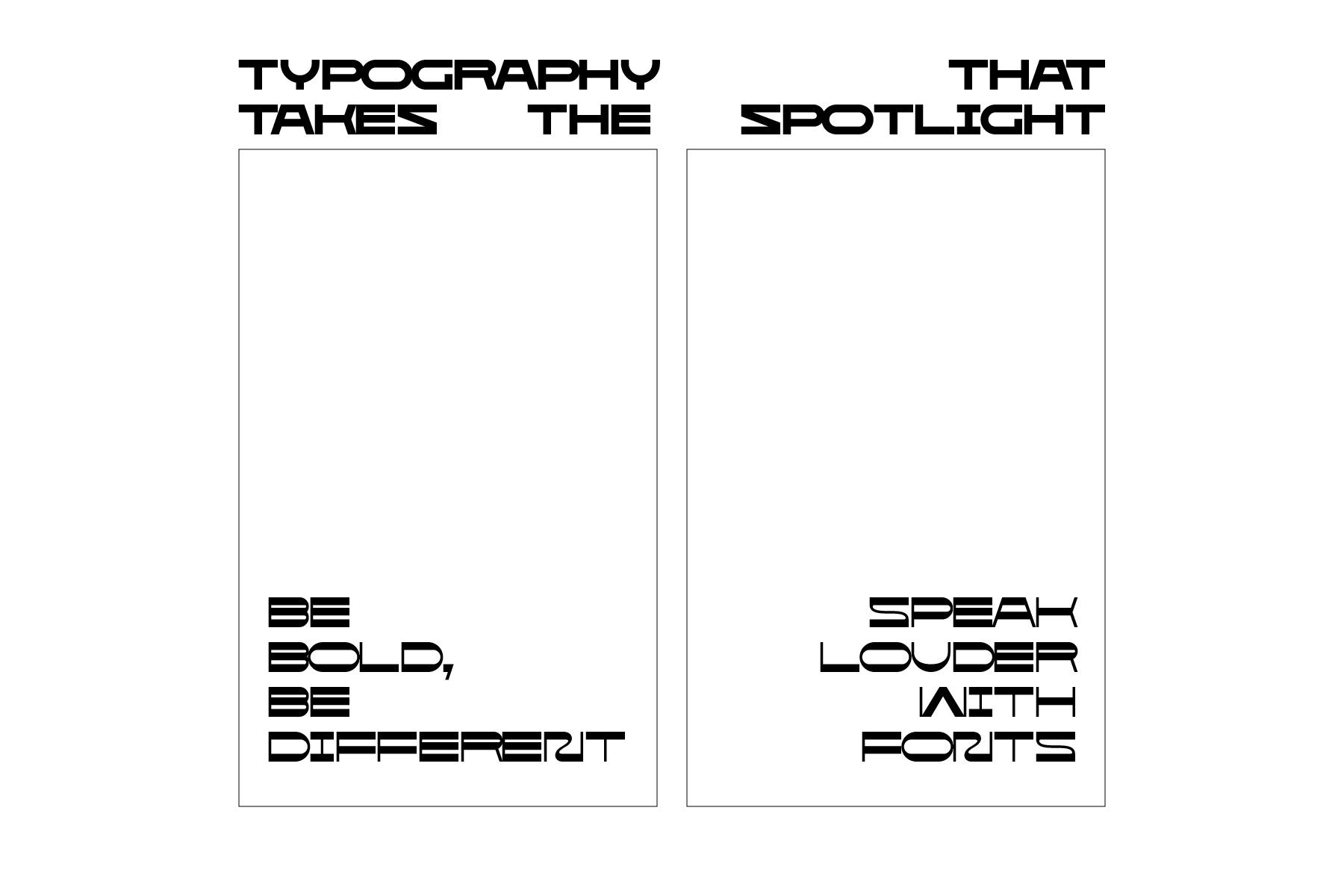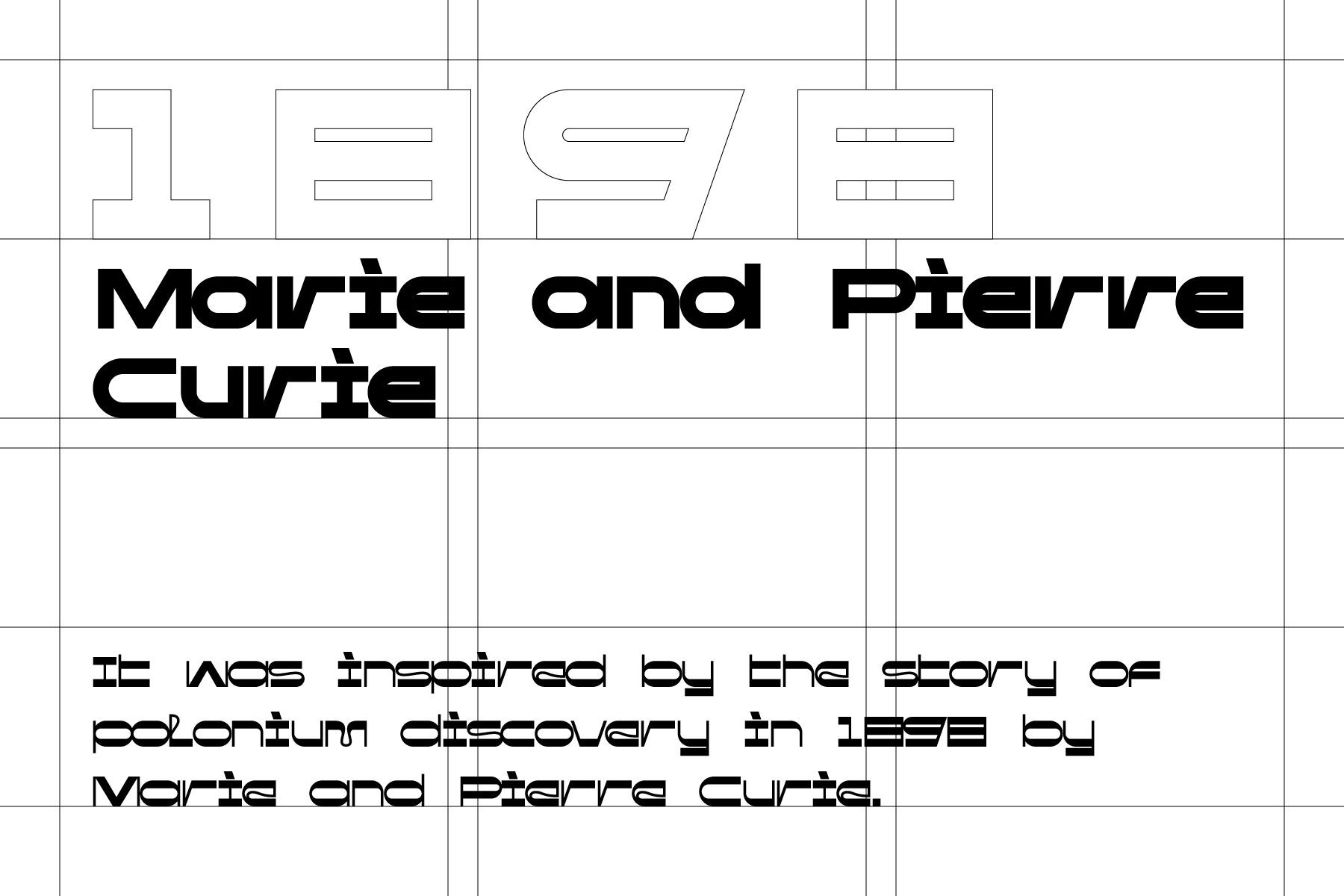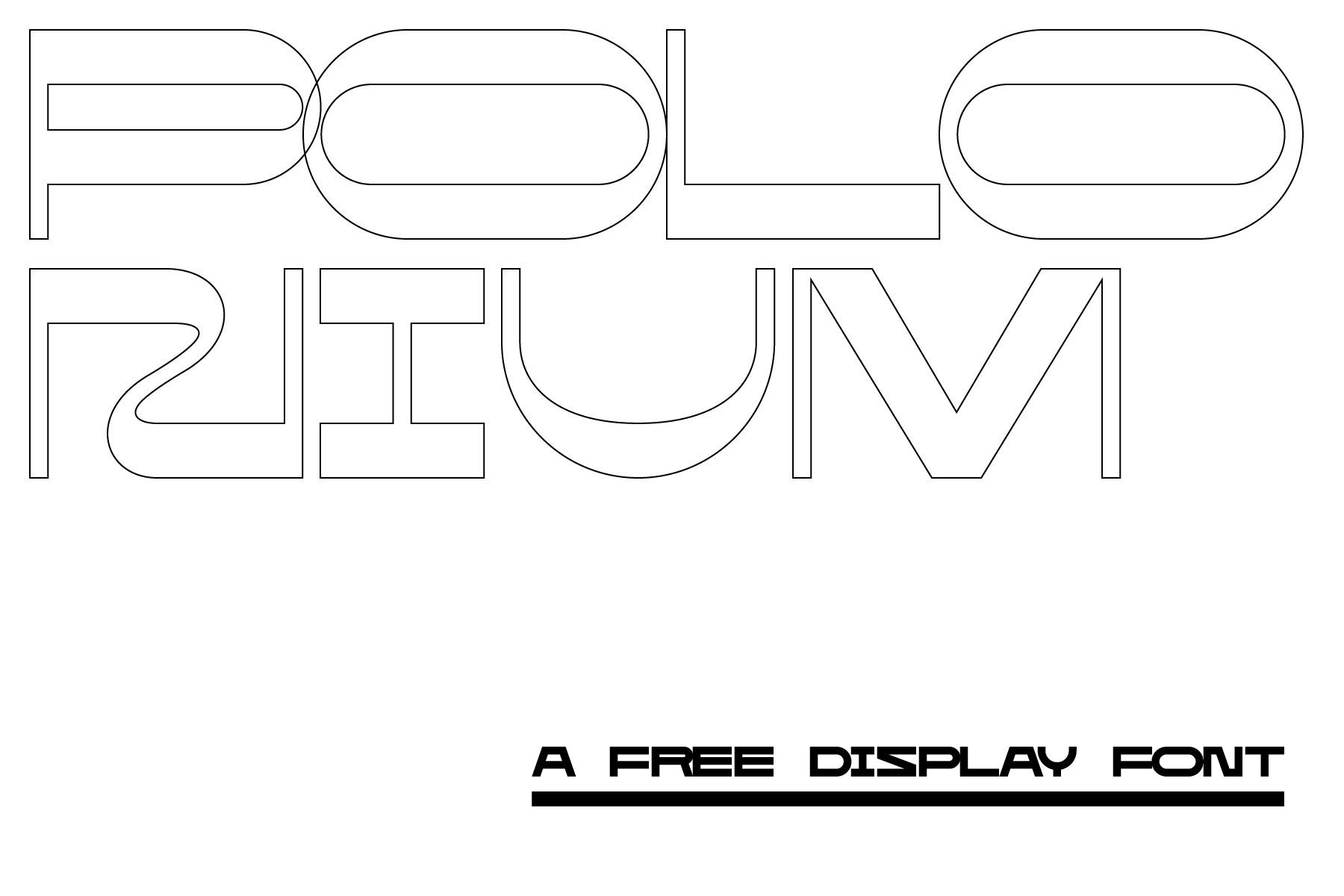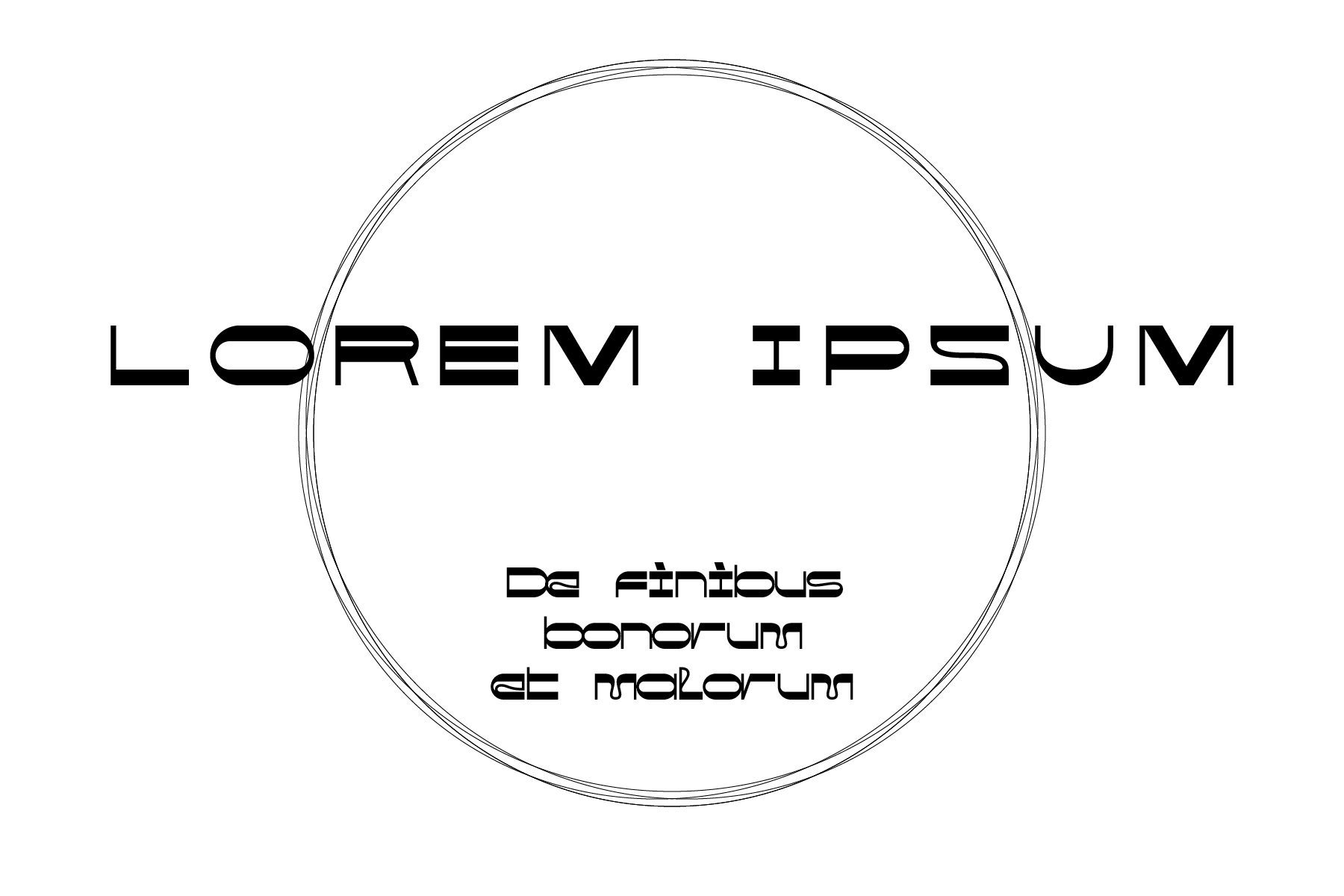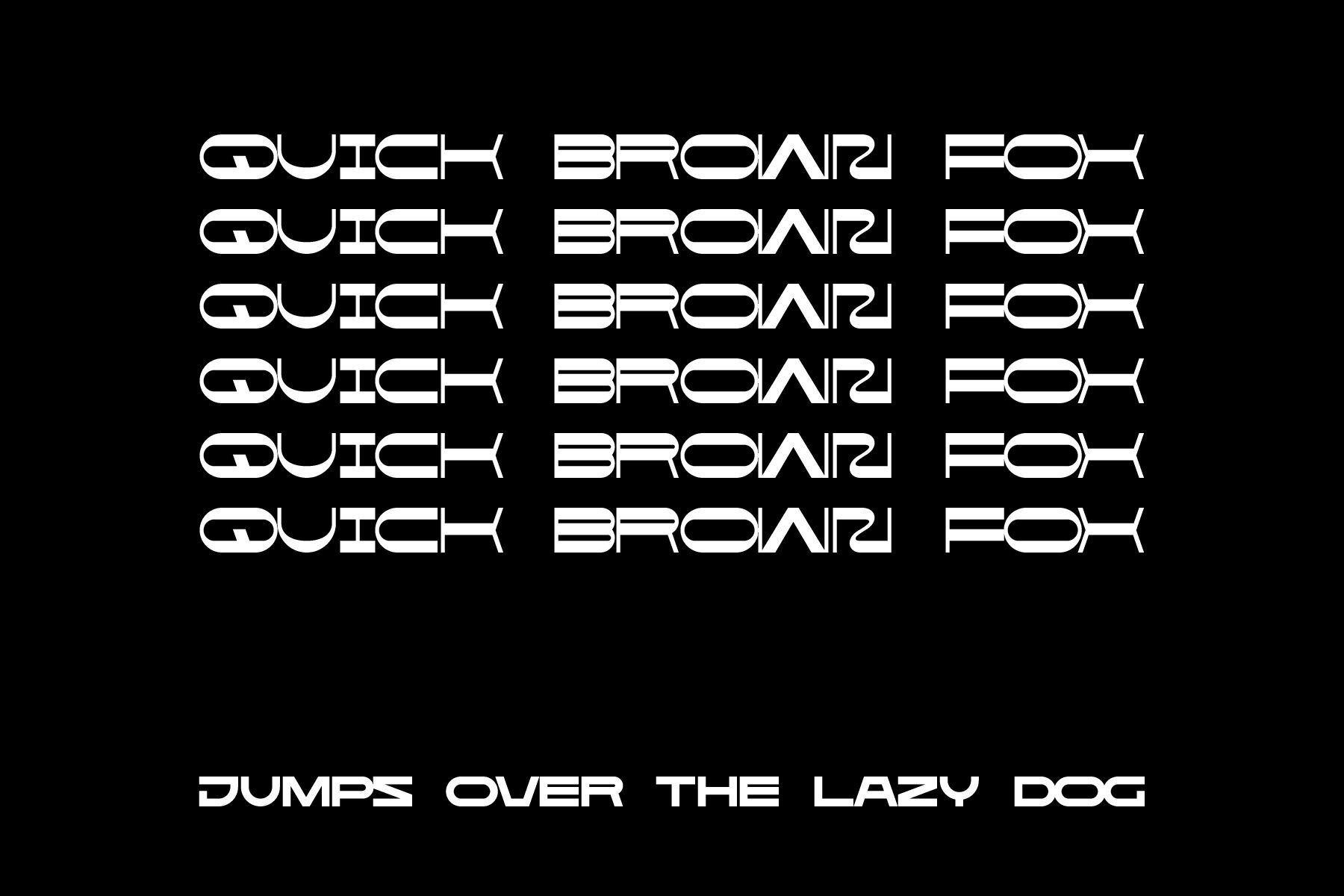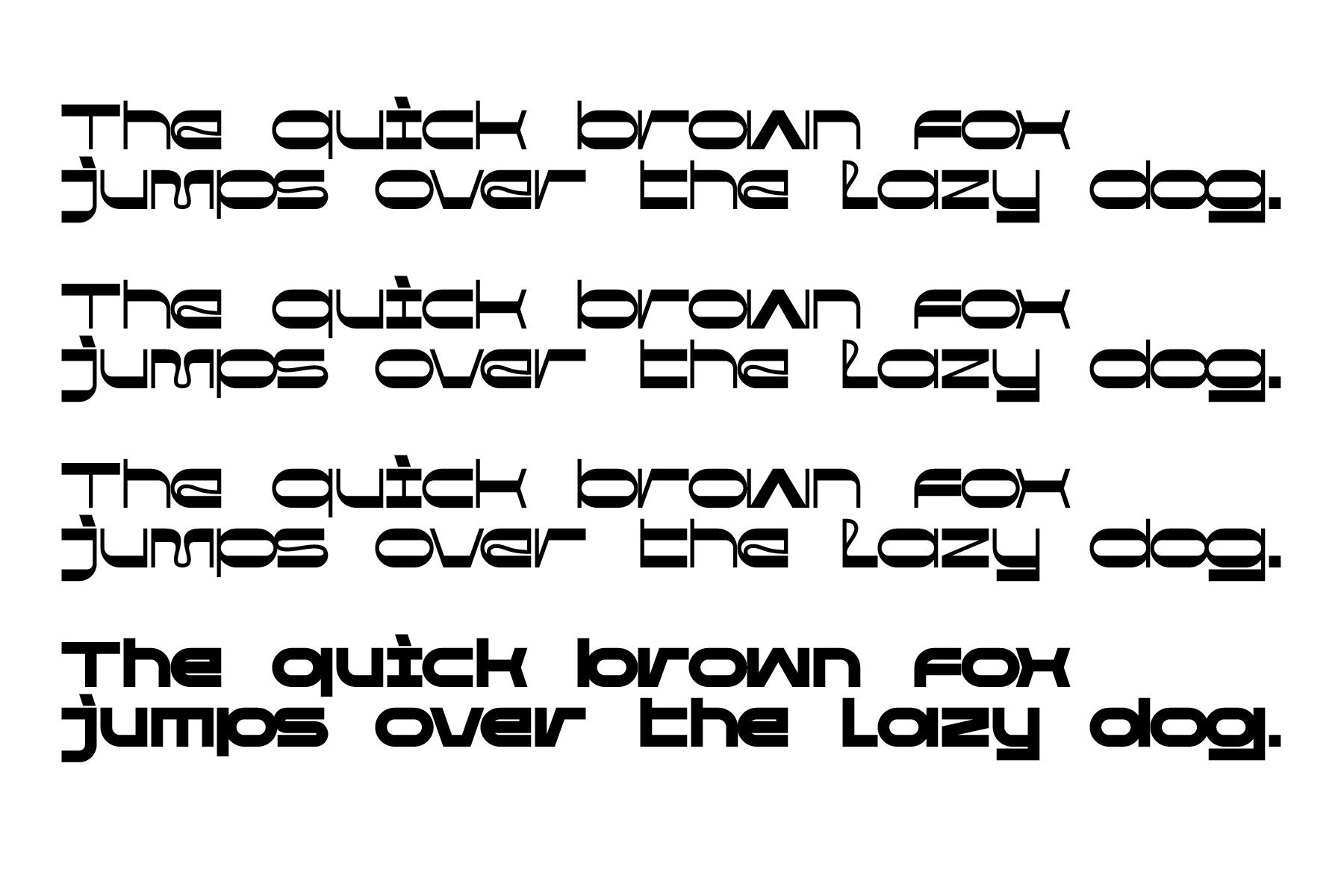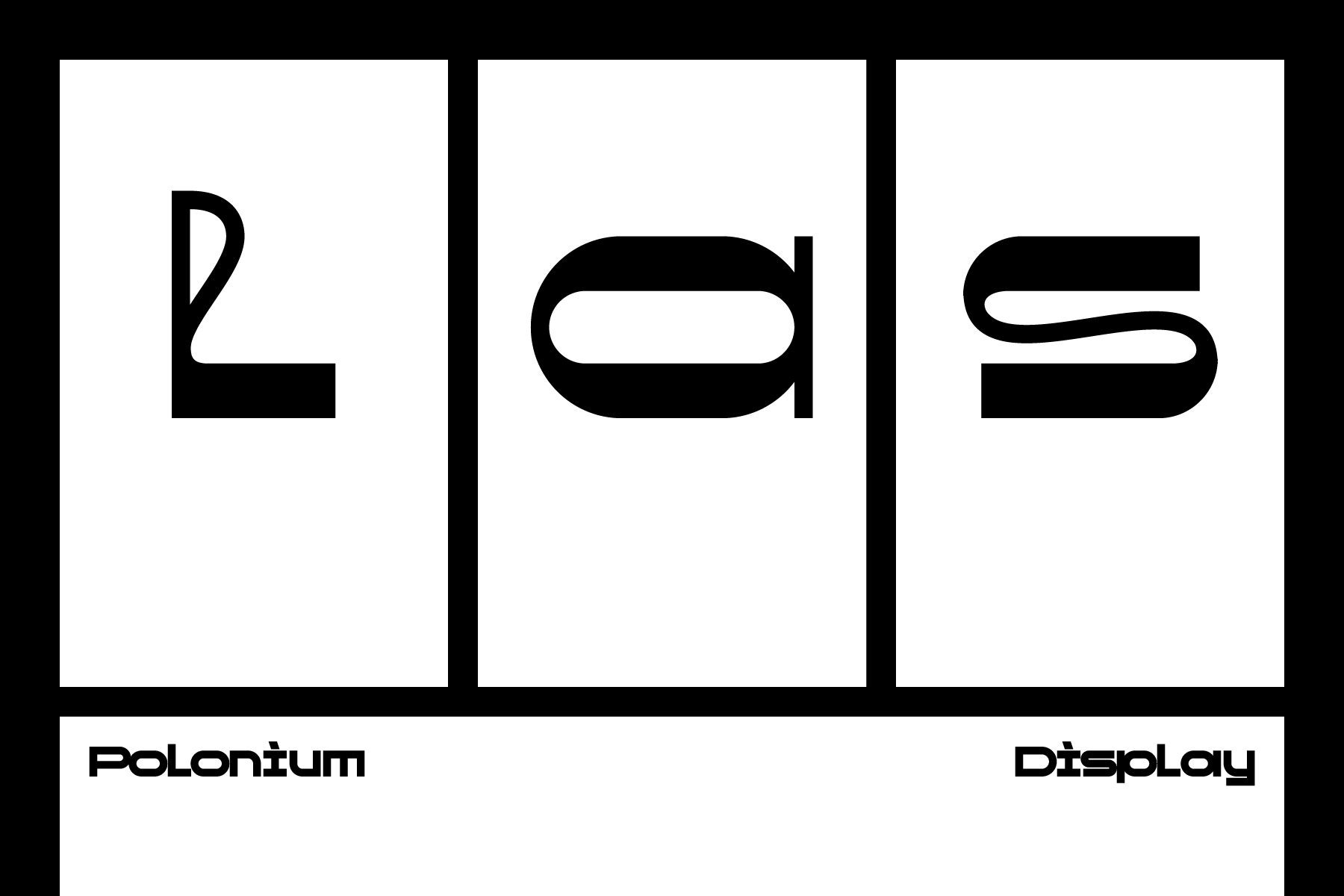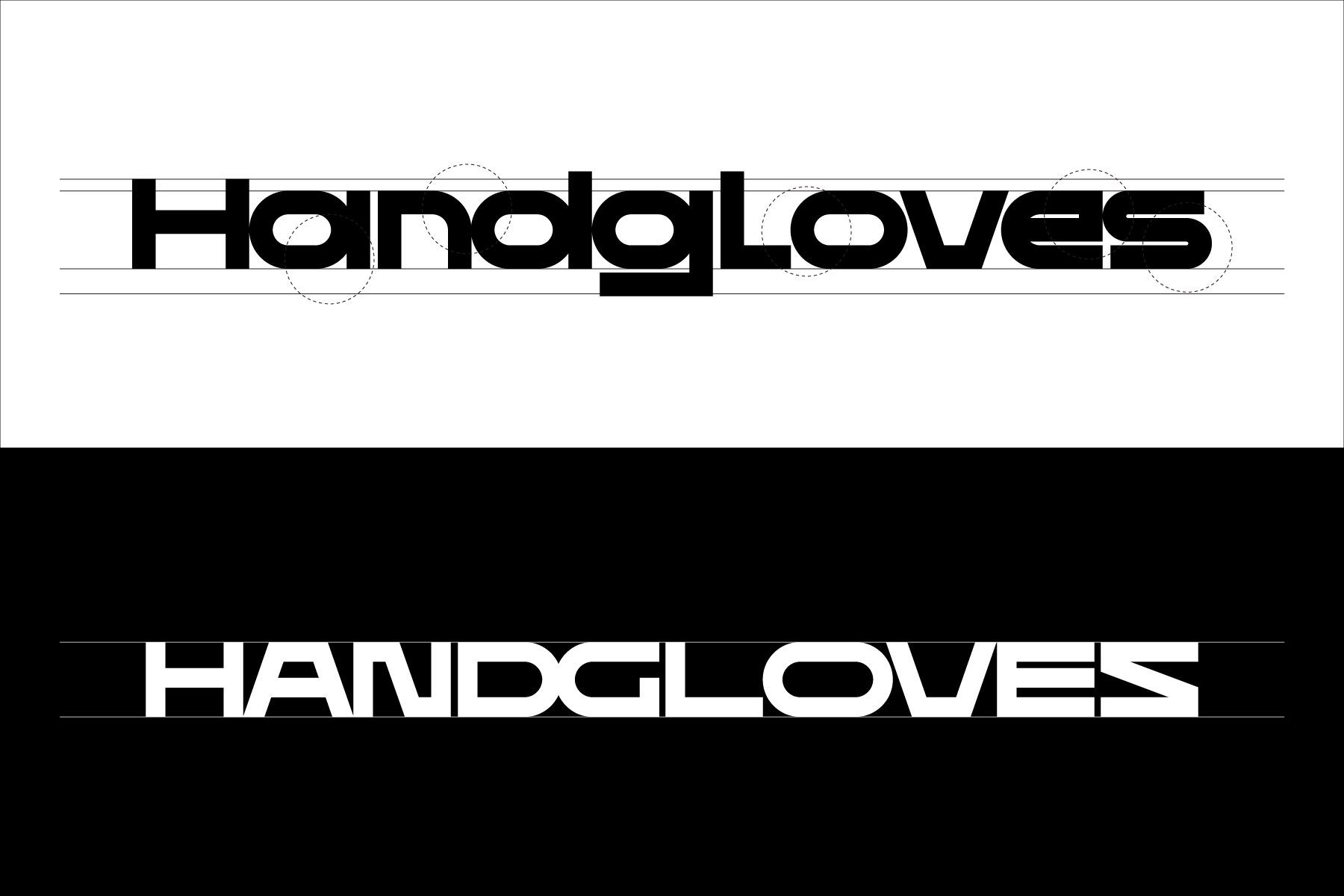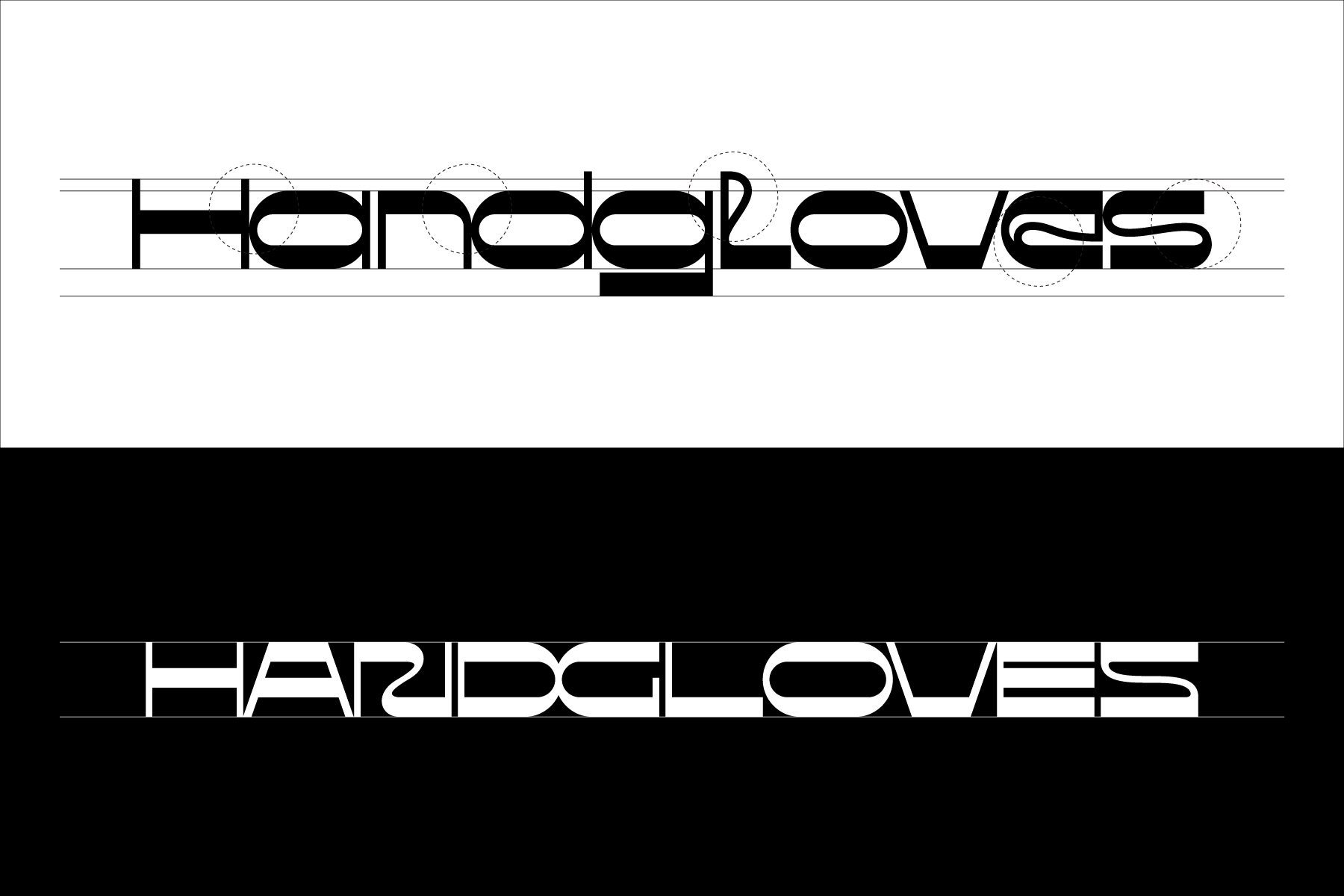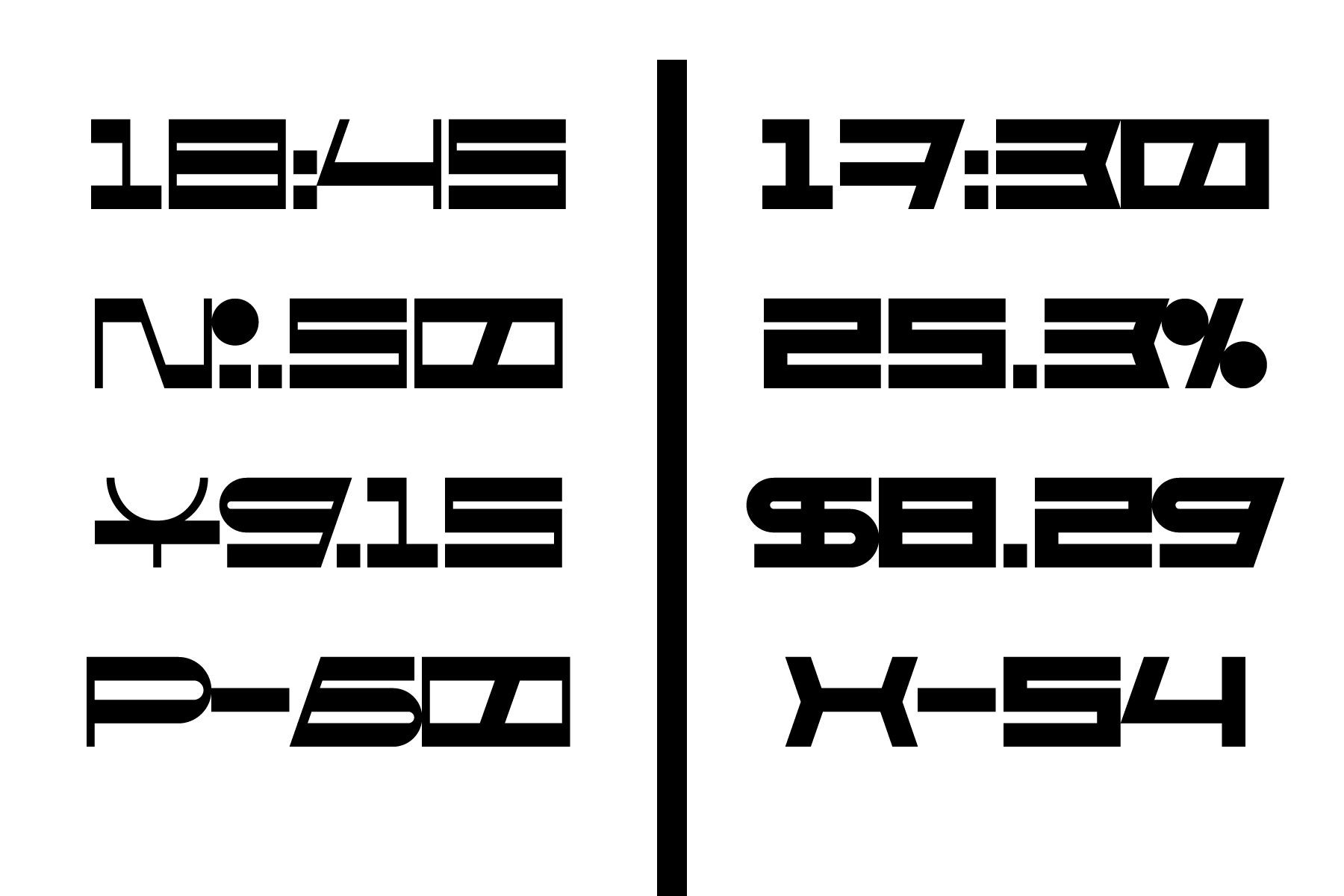
Nếu bạn đang tìm kiếm một font chữ độc đáo, cá tính mạnh để “quẩy” cùng style thiết kế Acid đang hot hit, thì không thể bỏ qua em Polonium này đâu nha!
Giới thiệu sơ qua về Polonium:
-
Nguồn gốc: Được tạo bởi Alexey Atapin.
-
Style: Siêu hiện đại, đậm chất trang trí (decorative), cá tính cực mạnh.
-
Ý nghĩa tên: Polonium chính là nguyên tố hóa học Poloni (Po) đó! Nghe tên thôi đã thấy “acid” rồi đúng không? 😉
Phân tích “nét chữ” Polonium:
-
Độ “hợp cạ” với Acid Design: Phải nói là 100%! Phong cách của Polonium cực kỳ ăn khớp với vibe méo mó, ảo diệu, đôi khi hơi “dị” của Acid Design.
-
Hai “anh em” Bold & Regular: Font này có 2 trọng lượng (weight) là Regular và Bold, nhưng không chỉ đơn giản là đậm nhạt đâu nha:
-
Bold: Nét chữ gần như đều nhau (monoline), trông khá “thô”, hình học, cứng cáp và đầy sức mạnh.
-
Regular: Có sự tương phản rõ rệt giữa nét dày và nét mỏng (ngang dày, dọc mỏng), tổng thể hình học nhưng lại có những đường cong uốn lượn, chảy, tạo cảm giác kim loại lỏng rất đặc trưng của Acid.
-
Bộ xương thống nhất, chi tiết khác biệt: Dù khác nhau về chi tiết, cấu trúc cơ bản của 2 weight này khá tương đồng, giúp chúng vừa có thể kết hợp ăn ý, vừa có thể đứng riêng lẻ phối với font khác mà vẫn nổi bật.
-
Kerning (Khoảng cách chữ) siêu “dính”: Mặc định khoảng cách giữa các chữ của Polonium rất hẹp, thậm chí có cặp chữ còn bị âm kerning. Điều này cộng với thiết kế ký tự độc đáo khiến font khó đọc hơn khi dùng ở cỡ chữ nhỏ.
-
“Sân khấu” lý tưởng: Vì là font display (trang trí), Polonium tỏa sáng nhất khi được dùng làm tiêu đề, bìa sách, poster… những nơi cần sự chú ý và hiệu ứng thị giác mạnh mẽ.
-
All Caps “cháy” hơn? Cá nhân tui thấy dùng toàn bộ chữ hoa (All Caps) với Polonium trông “ngầu” hơn, nhưng font vẫn đầy đủ chữ thường và các ký tự khác nha, không giới hạn sáng tạo đâu. Chữ ‘N’ hoa của font này thiết kế khá hay ho đó!
-
Độc lạ hàng free: Trong thế giới font miễn phí, Polonium thực sự là một “của hiếm”, vừa độc đáo, vừa thực dụng lại dễ nhận diện.
Khi nào nên “triệu hồi” Polonium?
Khi bạn cần một font chữ:
-
Hiện đại
-
Cá tính mạnh
-
Thu hút ánh mắt
-
Mang đậm vibe Acid Design
Thì Polonium chắc chắn là một lựa chọn đáng cân nhắc!